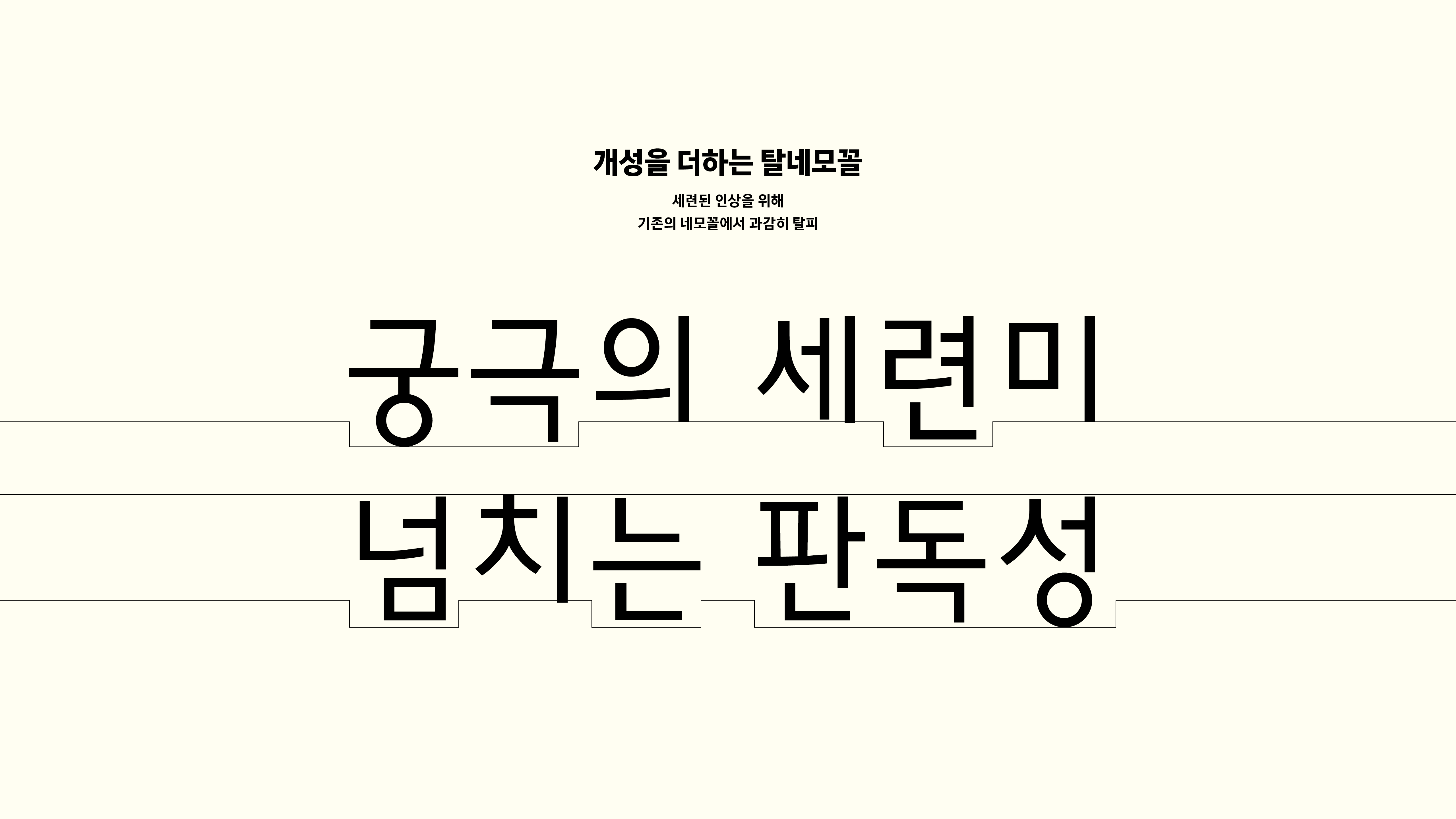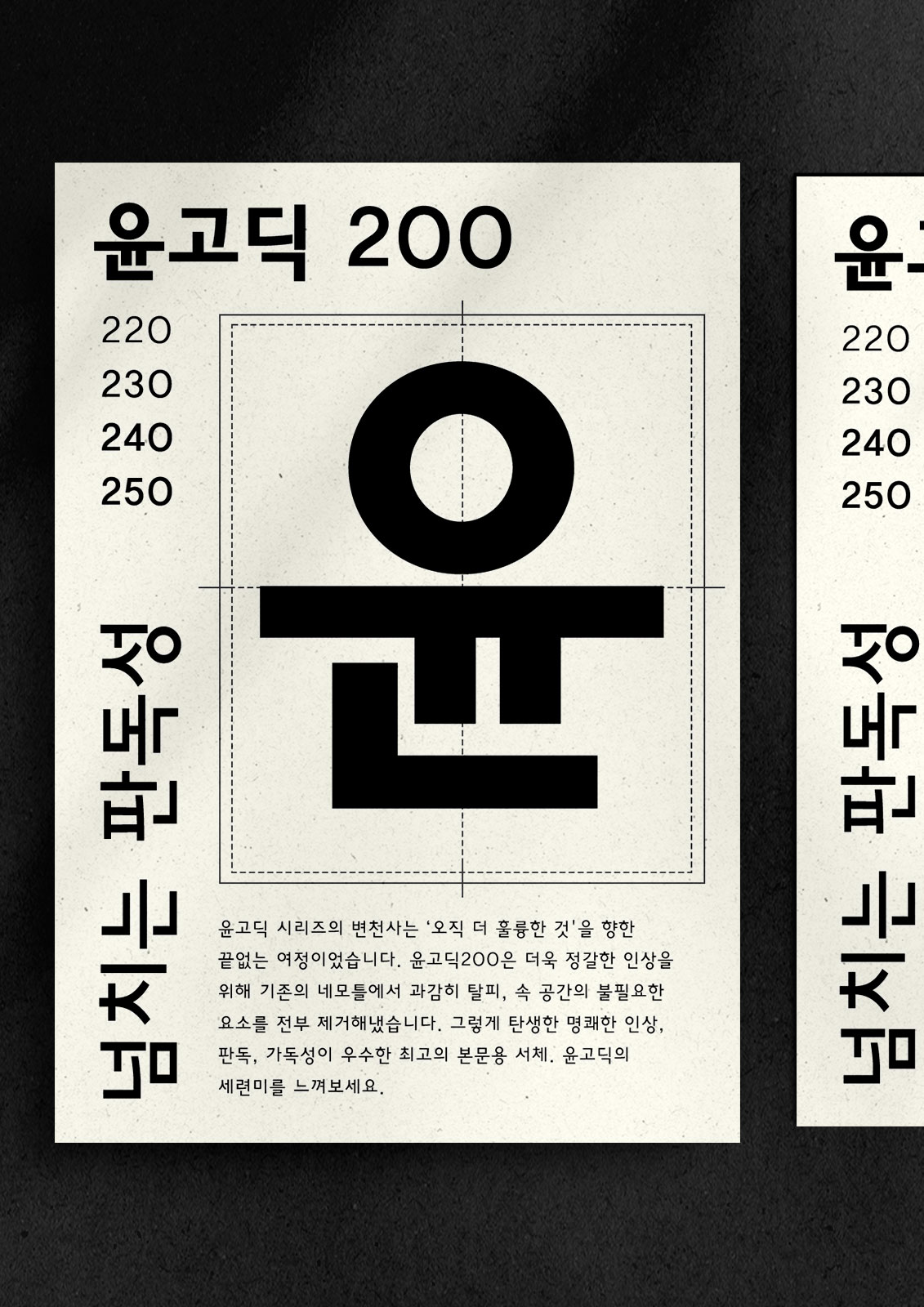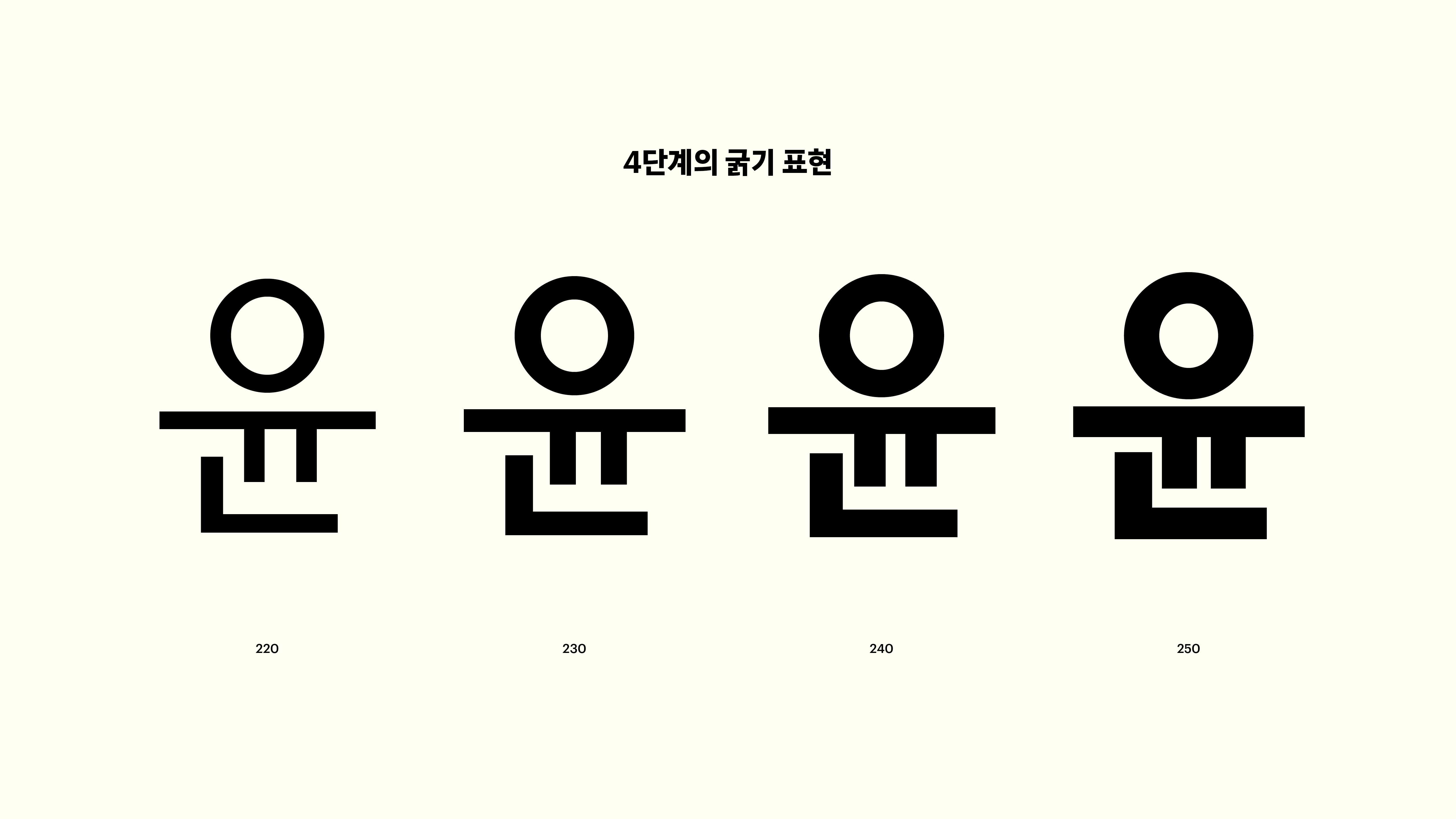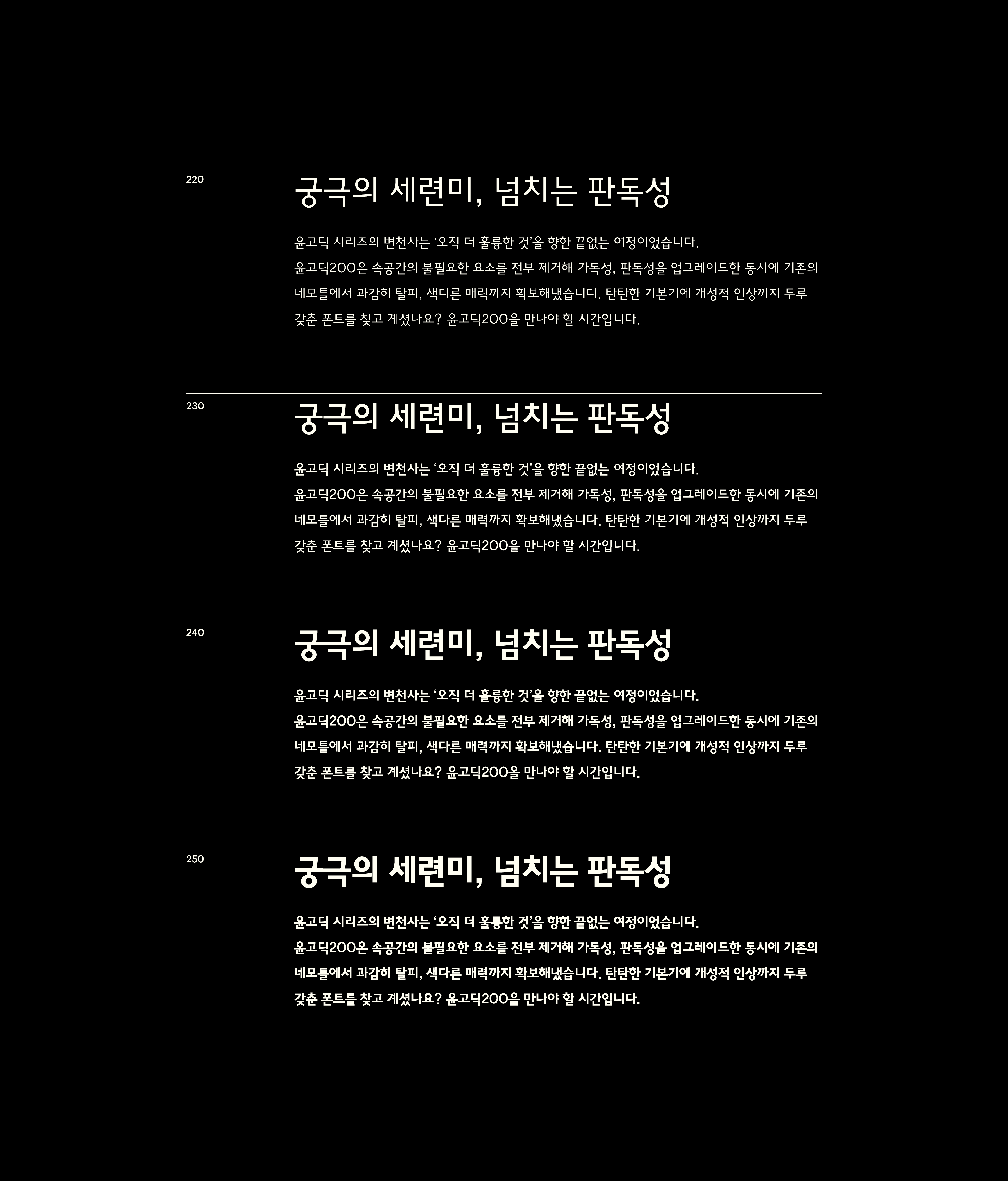
윤고딕 200
Yoon 윤고딕 200
윤고딕 시리즈의 변천사는 ‘오직 더 훌륭한 것'을 향한 끝없는 여정이었습니다. 윤고딕200은 더욱 정갈한 인상을 위해 기존의 네모틀에서 과감히 탈피, 속 공간의 불필요한 요소를 전부 제거해냈습니다. 그렇게 탄생한 명쾌한 인상, 판독, 가독성이 우수한 최고의 본문용 서체. 윤고딕의 세련미를 느껴보세요.